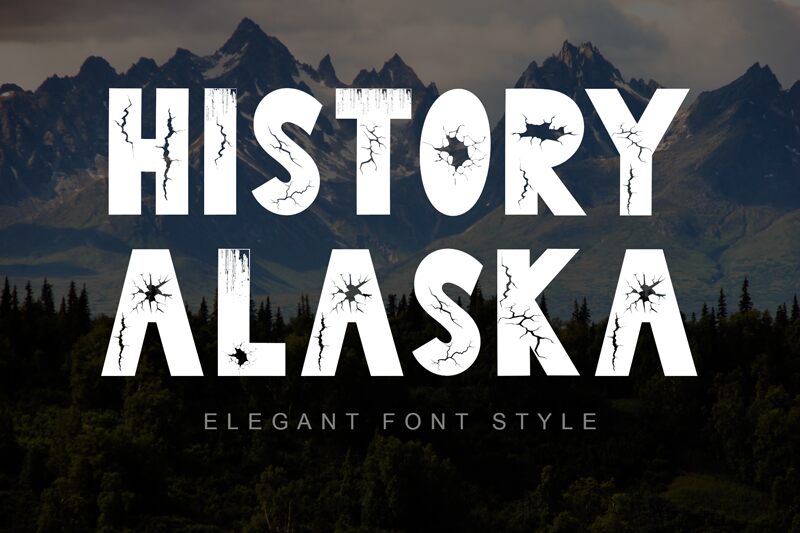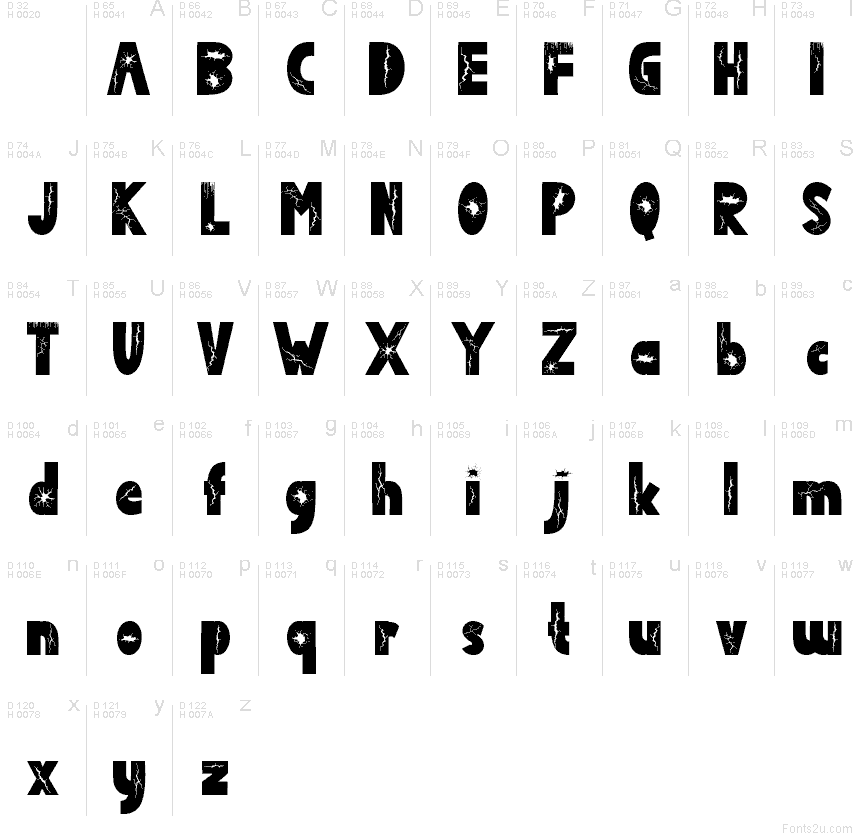
History Alaska
History Alaska de Yoga Letter es una tipografía display gratuita y distorsionada, con letras fracturadas y detalles de cortes afilados en cada trazo. Estas roturas se sienten desiguales y artesanales, otorgando al diseño un acabado rudo y desgastado que apuesta más por la textura que por el adorno.
History Alaska funciona de maravilla en títulos de pósteres, arte de álbumes, marcas de aventura, folletos de eventos invernales y gráficos de videojuegos que busquen un tono rudo y dañado. Esta fuente gratuita mantiene una estructura lo suficientemente sólida como para ser funcional, mientras que sus cortes fracturados la convierten en una opción contundente para logotipos cortos, portadas, diseños de etiquetas y elementos decorativos en banners.